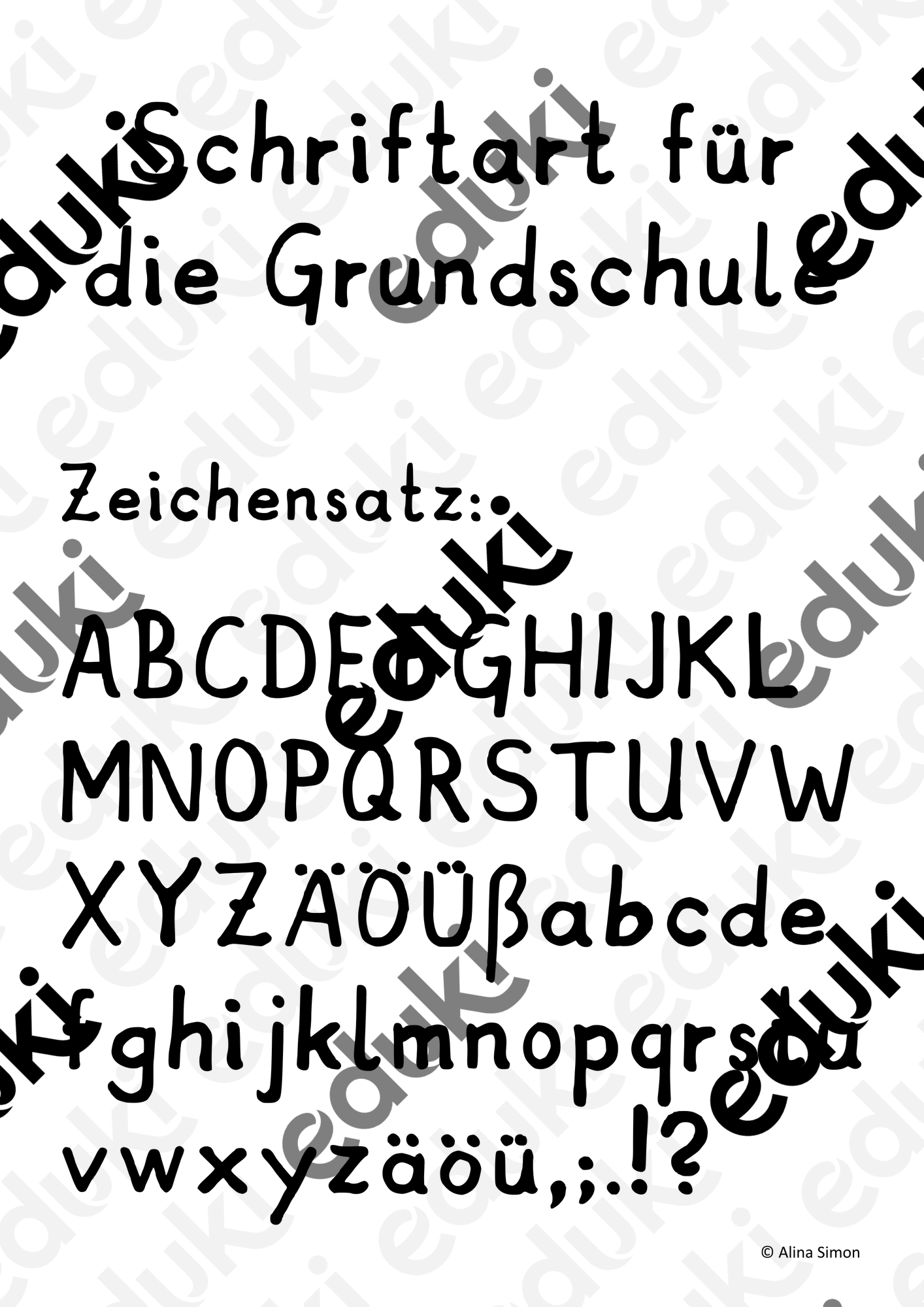
Diese Schriftart habe ich erstellt, um meine Materialien auch für Erstleser optimal lesbar zu machen.
ACHTUNG: Da meine technischen Möglichkeiten begrenzt sind, beinhaltet der Schriftsatz nur folgende Zeichen
ABCDEFGHIJKLMNOPQRSTUVWXYZ ÄÖÜß
abcdefghijklmnopqrstuvwxyz äöü
,;.!?